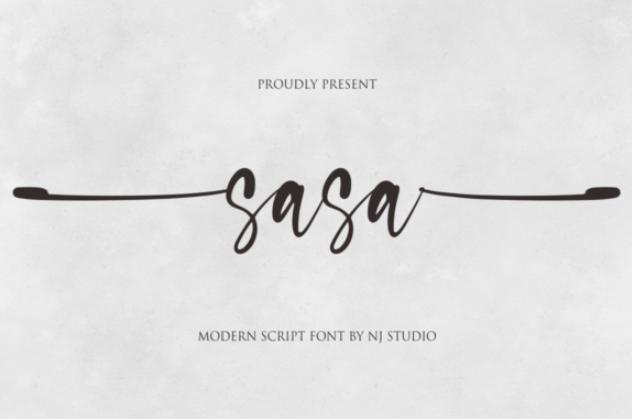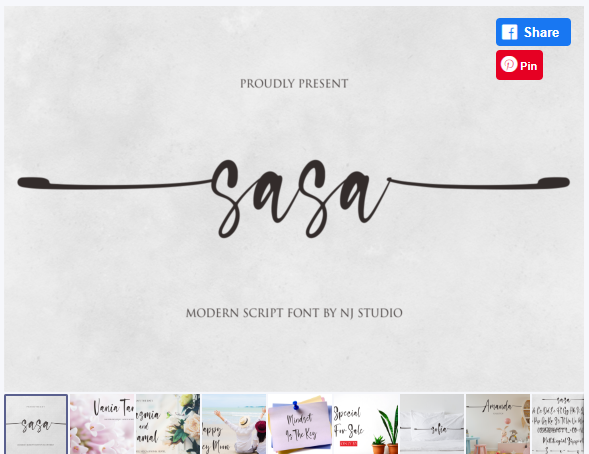
[Creativefabrica] Sasa Font (NJStudio)
Sasa - это изысканный рукописный шрифт, мастерски разработанный, чтобы стать настоящим фаворитом. Этот шрифт имеет кодировку PUA, что означает, что вы можете легко получить доступ ко всем глифам и росчеркам! Подпадайте под его восхитительный стиль и используйте его.